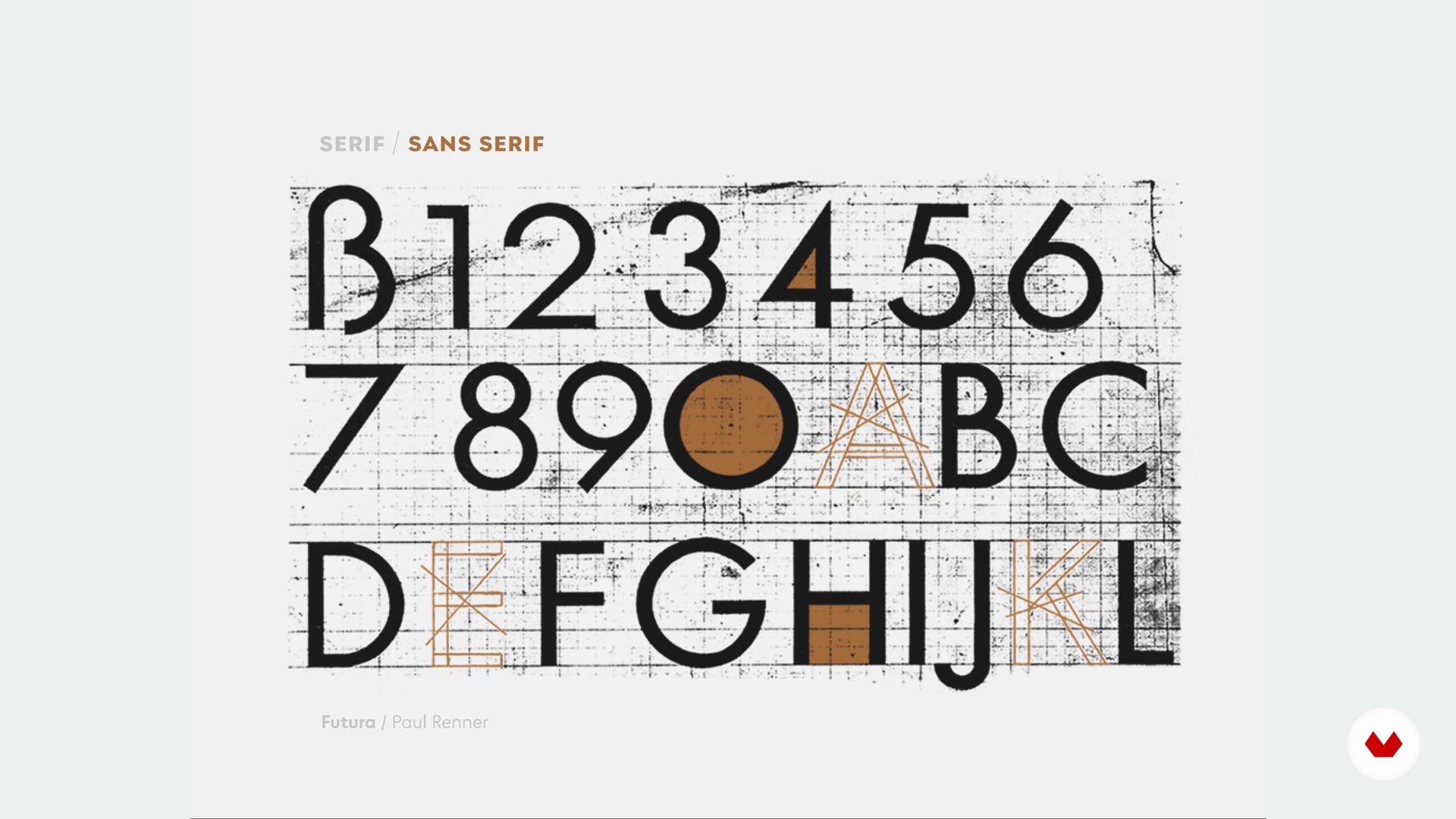
Principes élémentaires du design typographique
Anatomie de l'alphabet latin
À propos de la leçon : Anatomie de l'alphabet latin
“Nous montrons les éléments qui composent les caractères typographiques et leurs principales caractéristiques, afin que vous puissiez les identifier et les différencier.”
Dans cette leçon, Latinotype aborde le sujet : Anatomie de l'alphabet latin, qui fait partie du cours Domestika en ligne : Principes élémentaires du design typographique. Apprenez à créer votre propre alphabet modulaire avec Adobe Illustrator.
“C'est l'unité de base de la typographie. Dans cette leçon nous parlerons d'anatomie, nous saurons les caractéristiques et les pièces qui composent les lettres de l'alphabet latin. La première chose est de se diviser en deux grands groupes, afficher les polices et les polices de texte. Les affichages sont utilisés pour transmettre des concepts de par leur forme, ils sont utilisés en grandes tailles, logos, affiches, avec des textes courts et comme le dit Francisco Gálvez, ils doivent être vus et lus, leur forme doit connoter des choses. D'autre part, les polices de texte continu, sa fonction...”